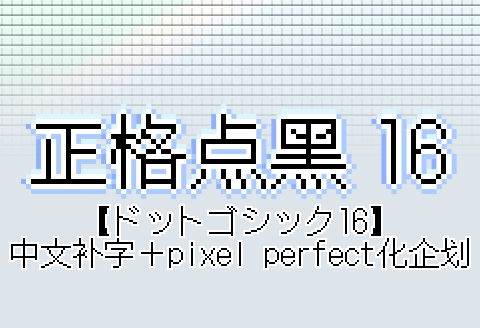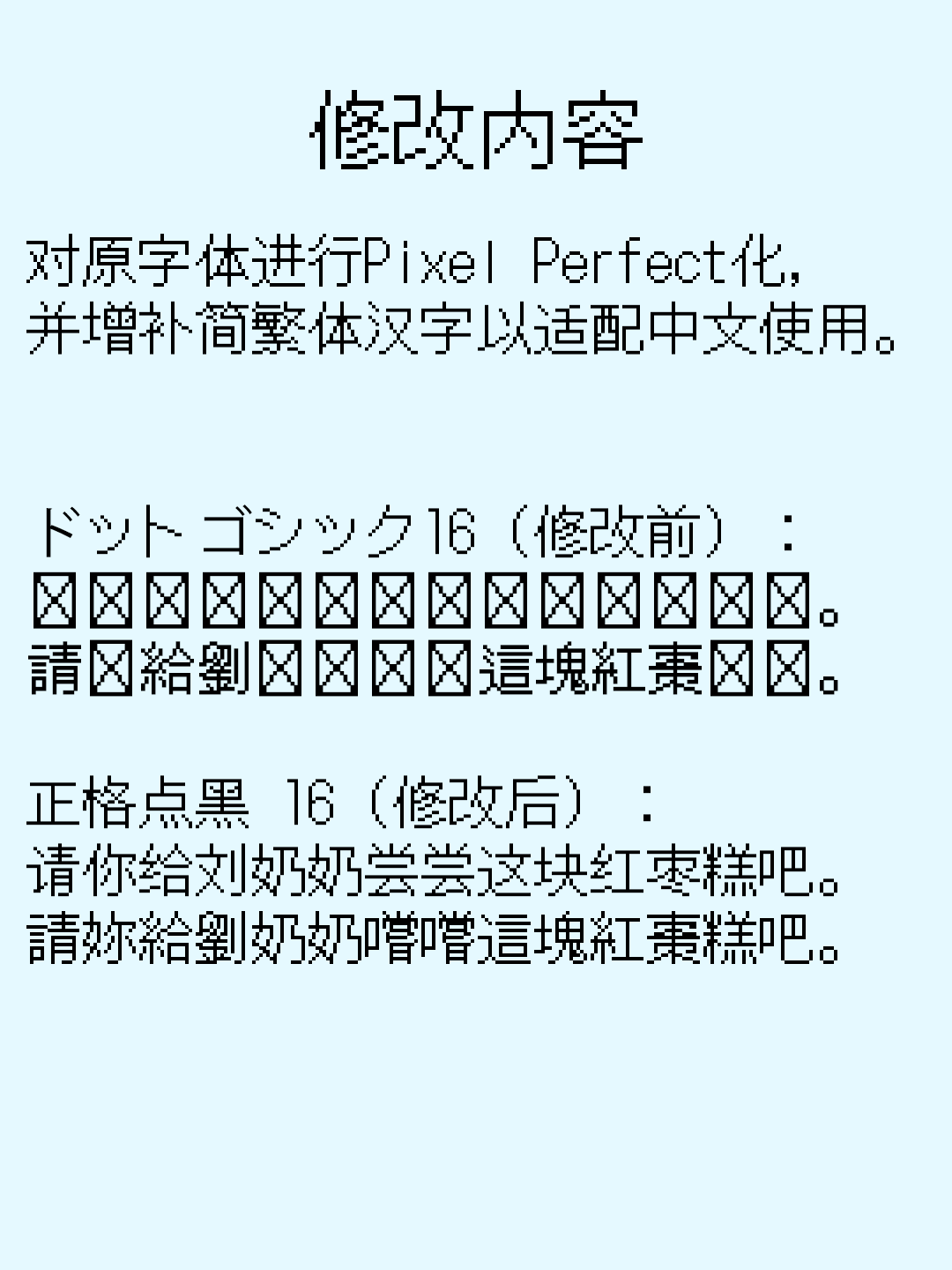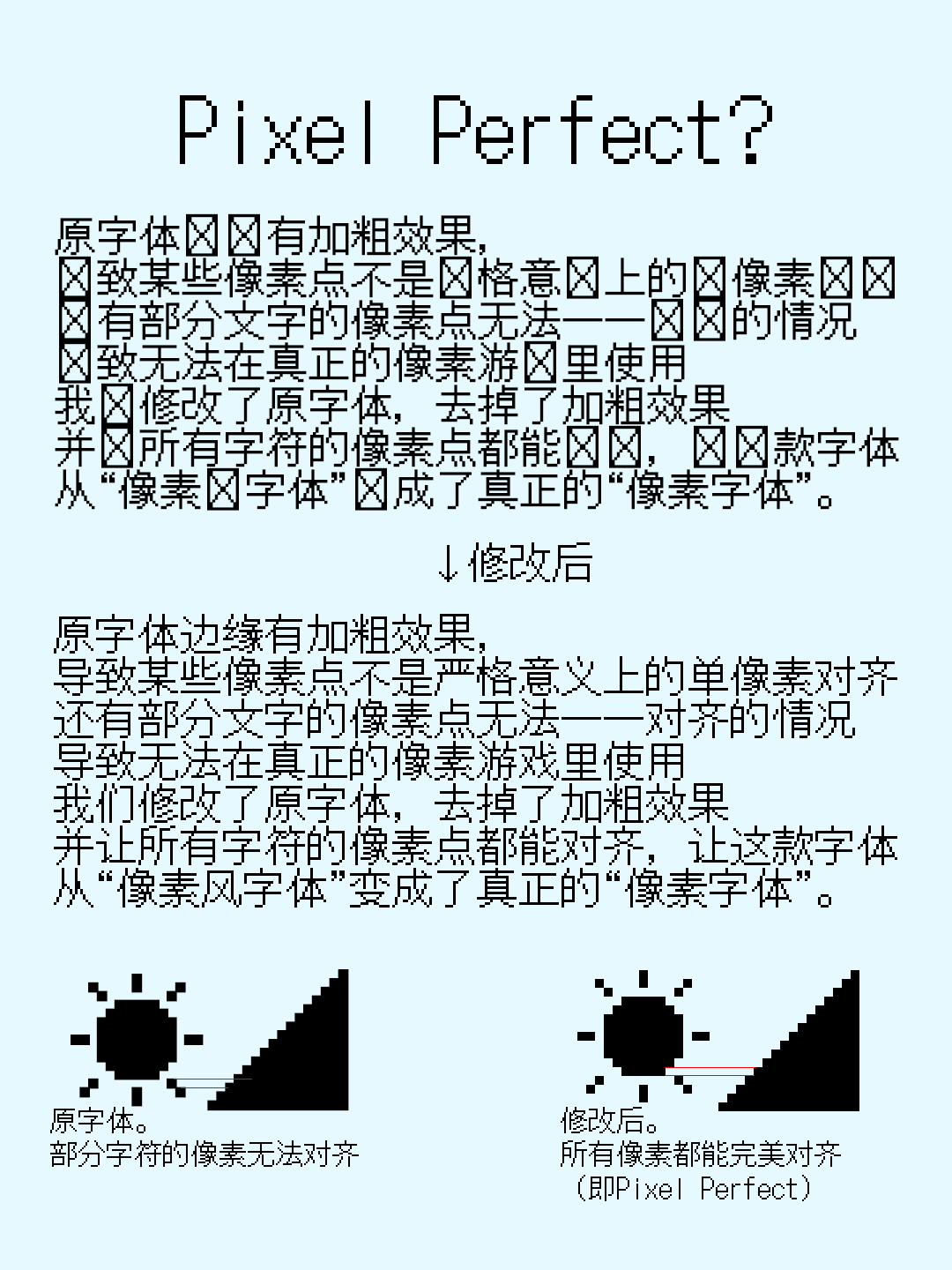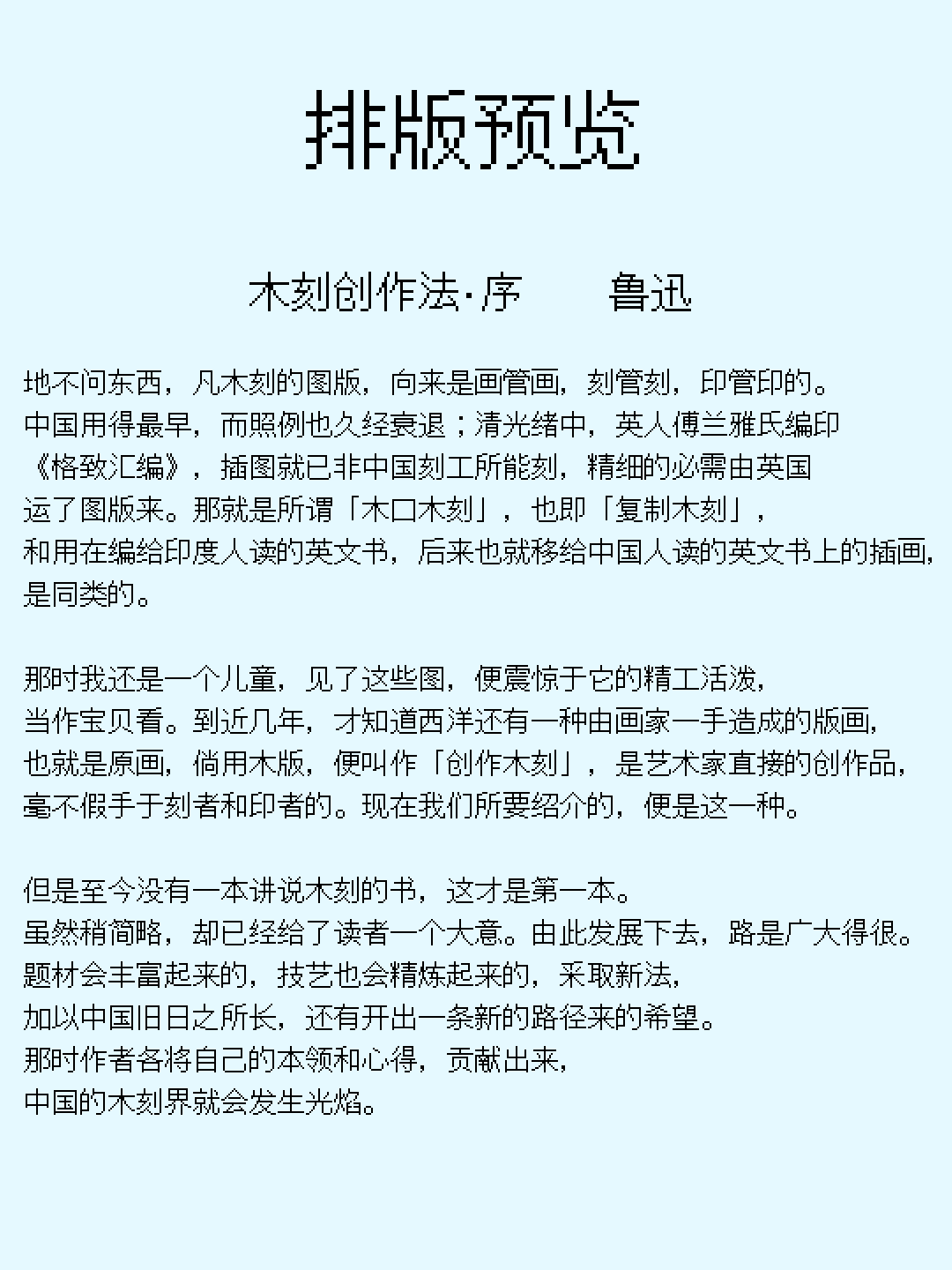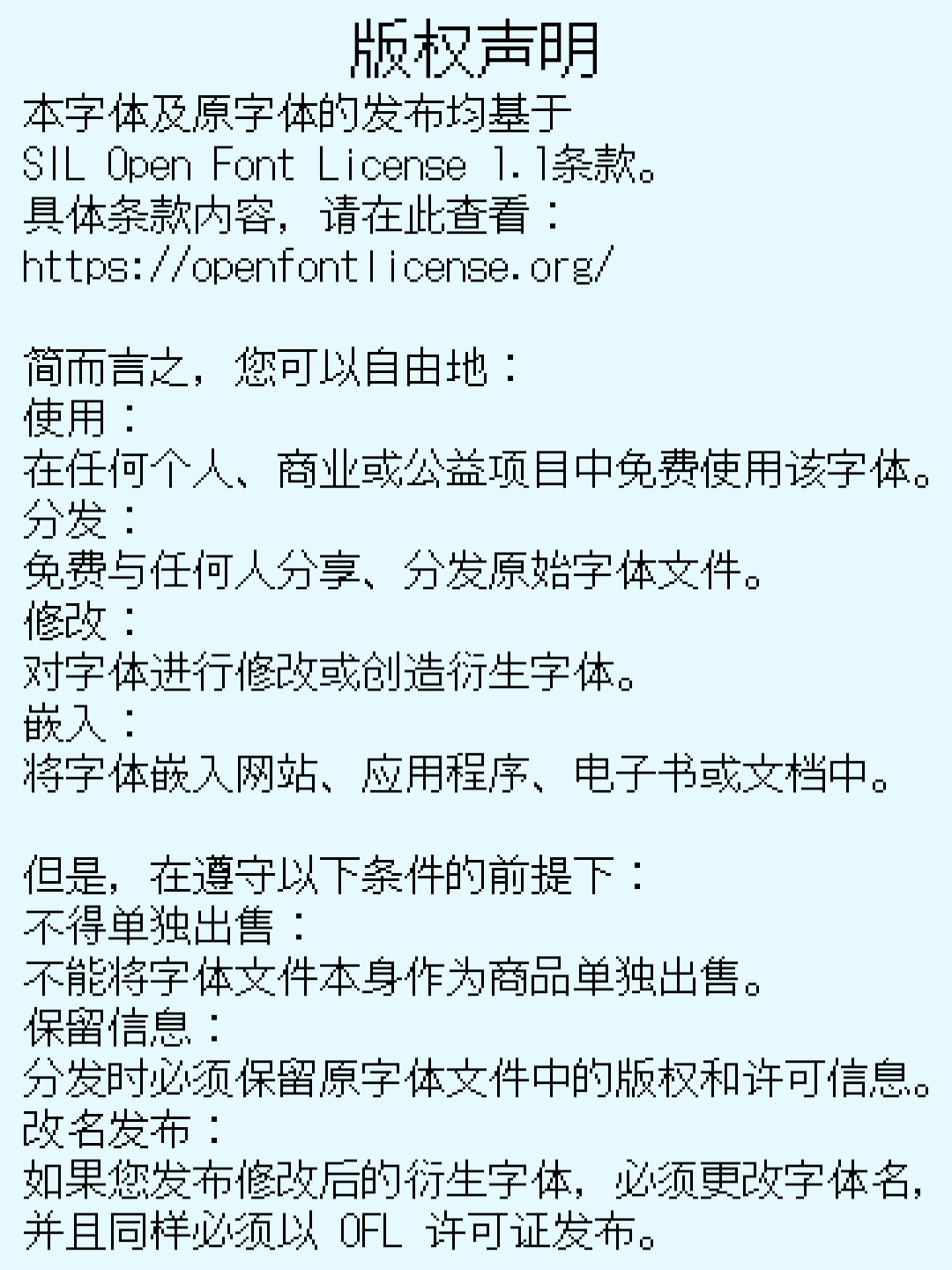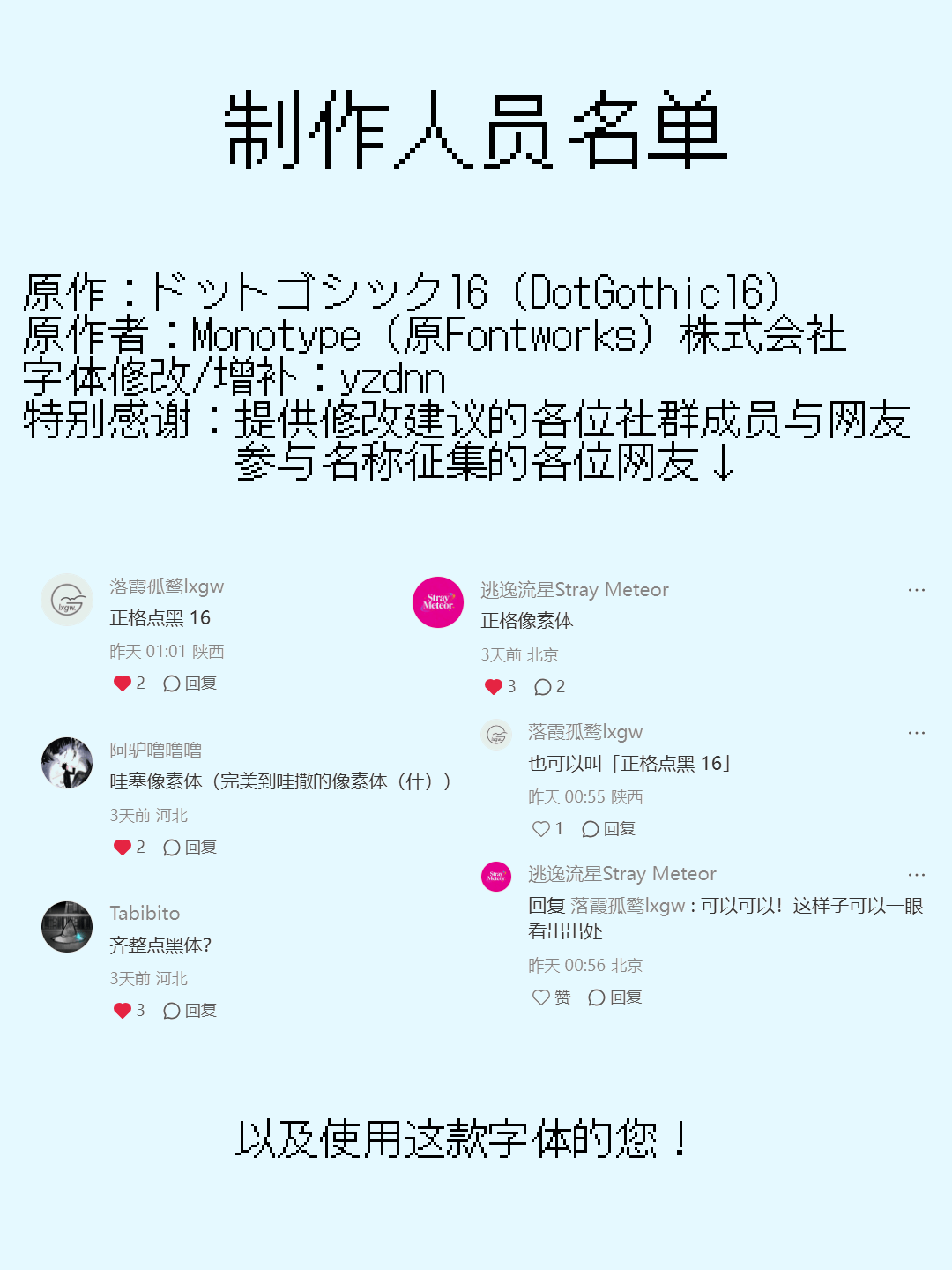
「正格点黑 16」是基于「ドットゴシック16」增补简繁体汉字的16px(含字间距)点阵黑体,适合在各种像素风场景使用。
熟悉像素字体/点阵字体的朋友都知道,日韩厂家的汉字点阵与我们常见的国标点阵的风格有所不同。(例如MS Gothic和Dotum的内嵌位图)
国标点阵有种宋黑折衷的风格,而日韩厂家做点阵字库时没有往宋体(明朝体)靠的习惯。
蒙纳(原Fontworks)的ドットゴシック16(DotGothic16)便是其中之一。
前几年这款字体在Google Fonts上和Fontworks的其他几款字体开始以SIL Open Font License授权发布,相当于开放了修改权限。
看到国内还没有这种风格的简体字点阵,于是我在做完袖珍像素体后,又开了这么个坑。
经过一番处理后,我成功将字体转换成了可以编辑的.bdf点阵,开始了漫长的补字之旅。
增补大量包含简化偏旁的汉字。
修改部分汉字的字形。
修复部分汉字(卢、屄、屌…)高度超过15px的问题。